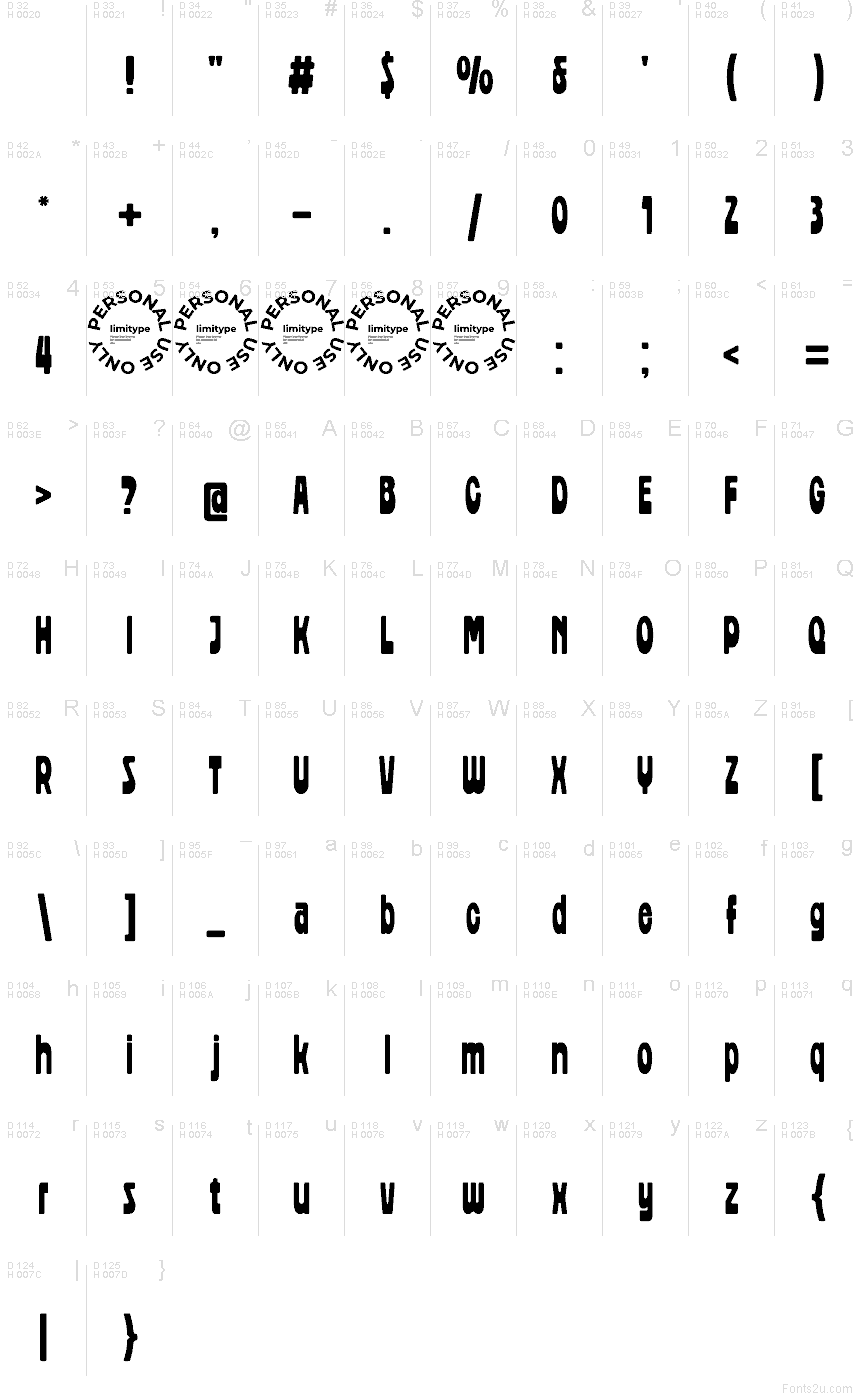
A Slovia da Limitype é uma fonte display sem serifa, gratuita e ultra condensada, com contornos arredondados e um visual impactante, típico de cartazes. As letras são altas, espessas e bem justas, com cantos suaves que impedem que as formas pesadas pareçam brutas, enquanto as formas ovais estreitas e as junções profundas conferem à fonte um ritmo que remete à sinalização retrô.